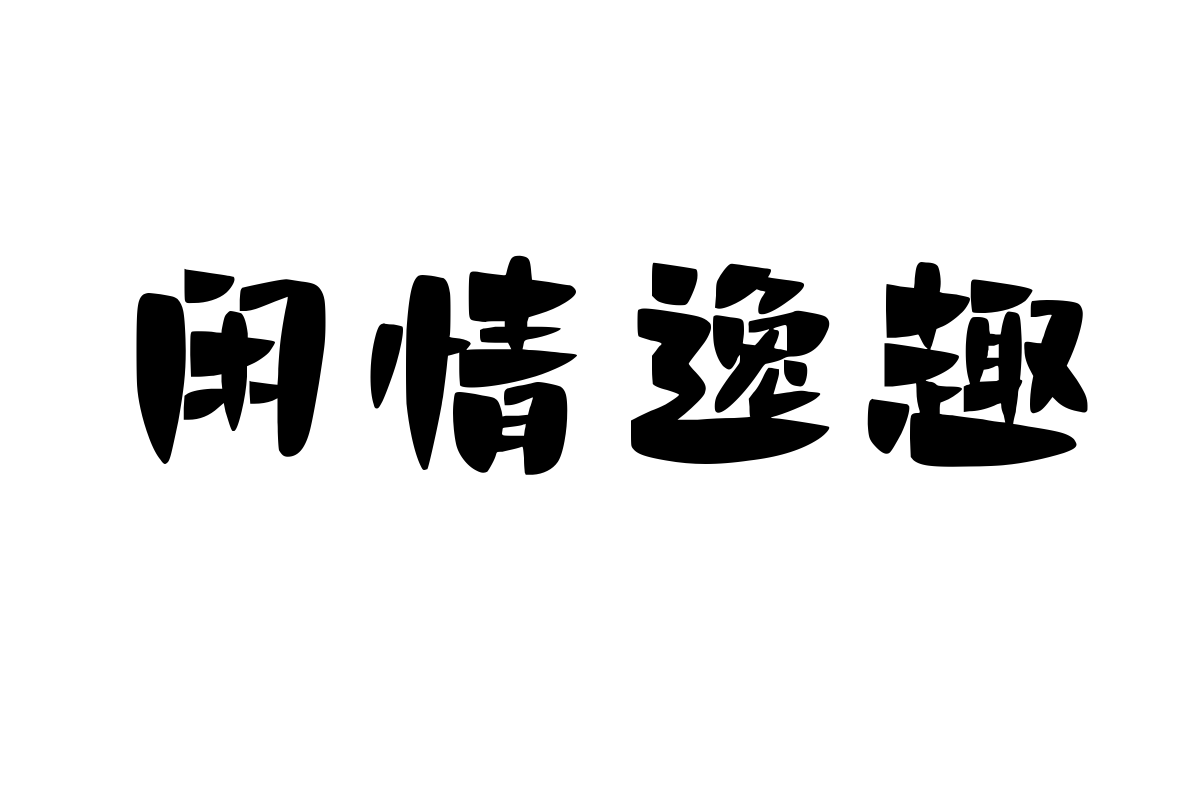
三极天涯体是一套具有独特风格的中文字体,由设计师陈晓明设计。它的特点是字形结构简洁、清晰,笔画粗细适中,整体风格优雅而富有艺术感。
该字体适用于各种印刷和电子媒体,如报纸、杂志、书籍、广告、网站等。它的应用场景广泛,可以用于标题、正文、装饰性文字等。
三极天涯体的设计理念源于中国传统书法艺术,融合了现代审美观念,旨在为读者提供一种既传统又时尚的视觉体验。